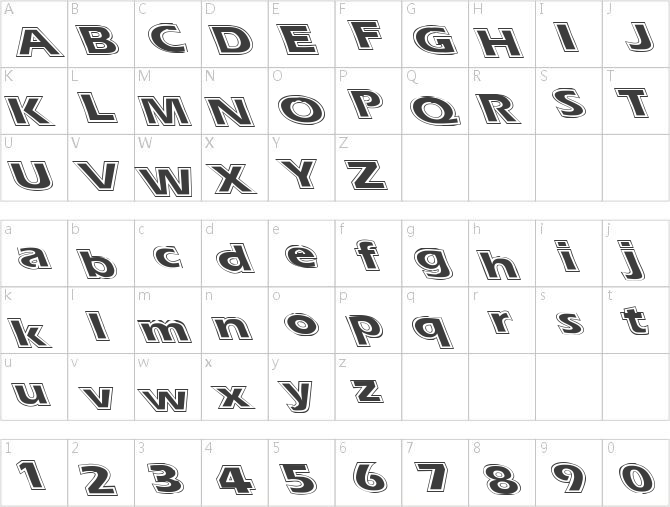
Eras-Contour-Lefty-Wide
Eras-Contour-Lefty-Wide介绍
Eras-Contour-Lefty-Wide字体字库是一款让人赏心悦目、百看不厌的英文字体,适合各类广告和产品包装设计应用,字体大小0.08MB,格式为ttf字体,上传用户是雅迪,作者/版权方为未知